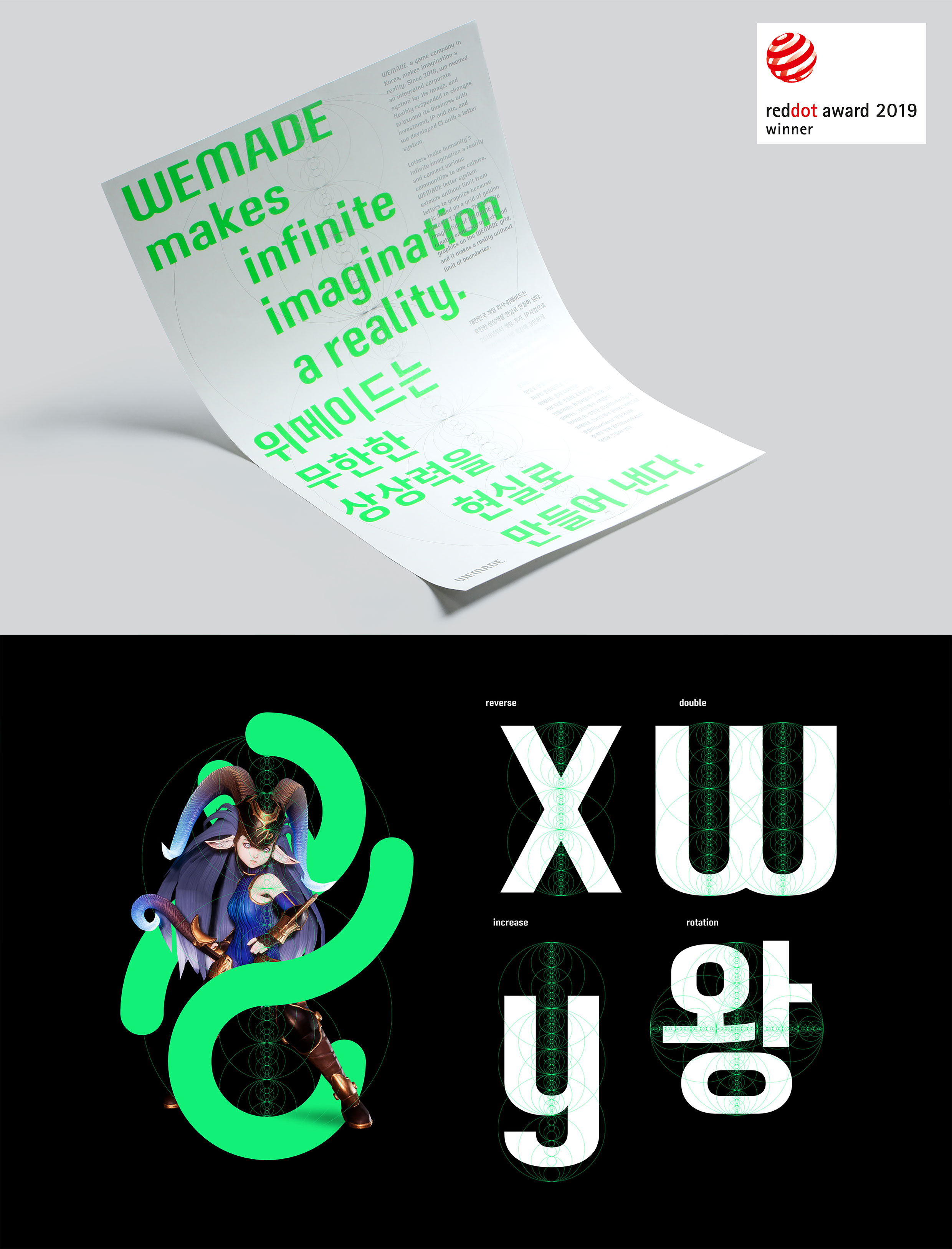
㈜윤디자인그룹, 위메이드 기업 CI와 전용 서체로 ‘2019 레드닷 디자인 어워드’ 수상
‘2019 레드닷 디자인 어워드’ 브랜드&커뮤니케이션 부문 본상을 수상한 위메이드 기업의 전용 서체 '인피니티 산스'
타이포 디자인 전문 기업 ㈜윤디자인그룹(대표 편석훈)은 자사가 개발한 위메이드 기업의 CI(Corporate Identity)와 전용 서체 인피니티 산스가 ‘2019 레드닷 디자인 어워드’ 브랜드&커뮤니케이션 부문 본상을 수상했다고 26일 밝혔다.
레드닷 디자인 어워드는 1955년부터 시작된 독일의 디자인 공모전으로 매해마다 제품, 브랜드&커뮤니케이션, 콘셉트 디자인 세부문을 평가하며 미국의 IDA, 독일의 iF어워드와 함께 세계 3대 디자인 어워드로 꼽힌다.
㈜윤디자인그룹은 위메이드 기업의 새로운 CI와 기업 전용 서체인 인피니티 산스를 개발했으며 기업의 이미지를 대표하는 CI를 심볼이 아닌 인피니티 산스 폰트로 디자인하여 전체적인 브랜딩을 강화한 점에 대해 호평을 받아 본상을 수상했다.
인피니티 산스는 다양한 요소를 조화롭게 연결하는 황금비율(1:1.618…)의 그리드가 특징으로 위메이드 고유의 개성 표현과 정확한 메시지 전달을 위해 높은 가독성을 가지고 있으며 ‘무한한 상상력을 현실로 만들어낸다’라는 위메이드의 정체성이 집대성된 글꼴 디자인이다. 위메이드는 사업 확장에 따라 유연한 대응과 일관된 기업 이미지를 유지하면서 그룹사들과 하나의 목소리를 내기 위해 ㈜윤디자인그룹과 함께 CI와 전용 폰트디자인을 개발함으로써 기업 아이덴티티를 재정립하는데 성공했다.